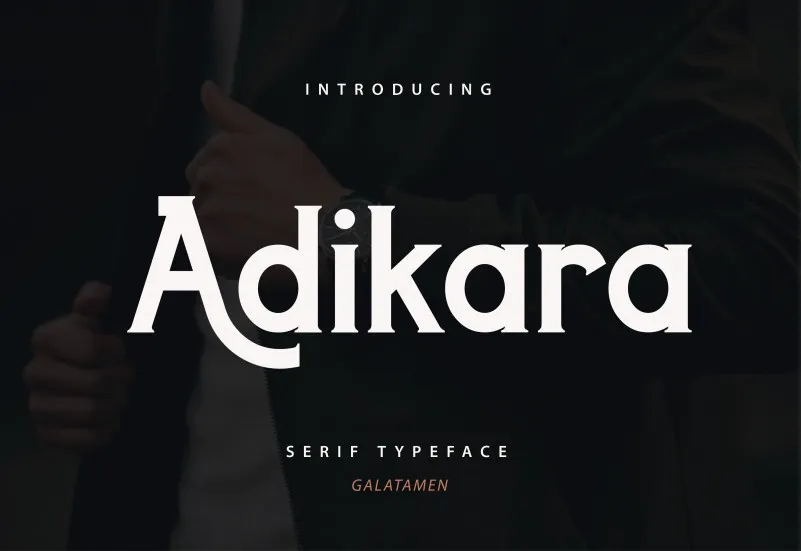
Adikara Font – Download Grátis
A Adikara Font é uma elegante fonte Serif com estilo robusto, cuidadosamente criada pela Galatamen para artistas e designers que buscam expressar seus ideais criativos de maneira sofisticada e profissional. Essa font se destaca por seu design cuidadosamente perfeito, oferecendo a capacidade única de levar suas invenções imaginativas à máxima excelência. Ideal para anúncios publicitários, gráficos impressos ou qualquer projeto visual que valorize estilo e qualidade, a Adikara Font é uma escolha estratégica para quem busca um toque de sofisticação em seus trabalhos. Não apenas funcionalmente perfeita, mas também capaz de transformar seu trabalho em algo verdadeiramente excepcional.